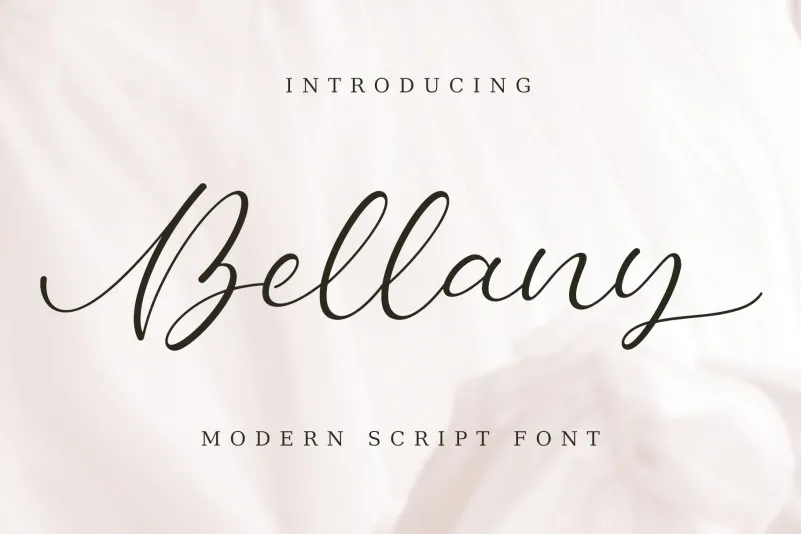
Bellany Script Font – Download Grátis
A Bellany Script Font é uma elegante solução para designers que buscam um estilo moderno e sofisticado para projetos diversos. Com seu traço arredondado e detalhes finos, ela se destaca especialmente em elementos como identidade de marca, cartões de convite, editoriais fashion, capas de livros e outros materiais de mídia social. Esta fonte é perfeita para criar um toque atraente em logos, mensagens de boas-vindas e qualquer outro projeto que exige uma aparição elegante. Seja você criando cartões de identidade modernos ou capa revigorantes de livros, Bellany Script Font será sua escolha perfeita para estilizar um projeto com um toque sofisticado e moderno.